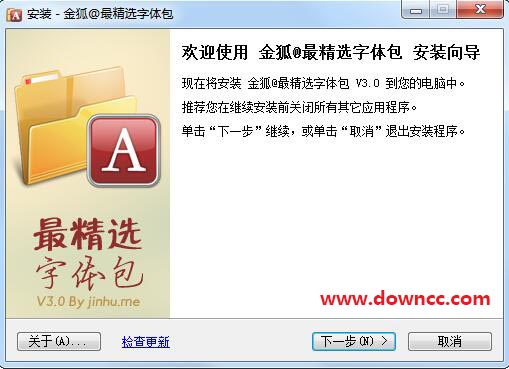
金狐精華字體包一共包含了408款最新的字體,字體分類明確,可以適用于設(shè)計(jì)、印刷、辦公等行業(yè)使用!能夠滿足多數(shù)用戶的不同字體需求!歡迎用戶在綠色資源網(wǎng)下載使用!
金狐精華字體包是一款經(jīng)典的字體應(yīng)用,這款最新版本的字體包是從三千多款各類字體里精挑細(xì)選,錄用408款,而且新包字體分類更加詳細(xì),適合從事網(wǎng)頁設(shè)計(jì)、辦公排版等行業(yè)用戶使用!
1.金狐精選字體這次更新作了比較大的調(diào)整,歷時一周左右,從三千多款各類字體里精挑細(xì)選,錄用408款,并根據(jù)字體的不同特點(diǎn)作了更詳細(xì)的分類。
2.包括“簡 體中文字體(91款)”、“繁體中文字體(18款)”、“精選英文字體(213款)”、“硬筆書法字體(9款)”、“數(shù)學(xué)公式字體(24款)”、“拼音樂 譜字體(10款)”、“圖案圖形字體(31款)”、“經(jīng)典像素字體(12款)”。
3.能夠輕松應(yīng)對日常辦公排版,亦能很大程度上滿足網(wǎng)頁設(shè)計(jì)和 文印等專業(yè)設(shè)計(jì)的需求。